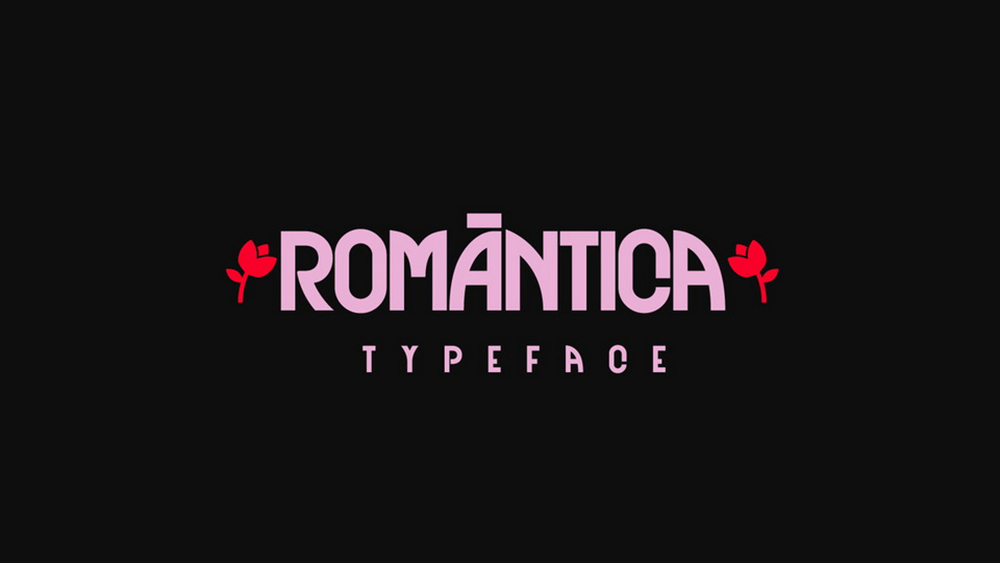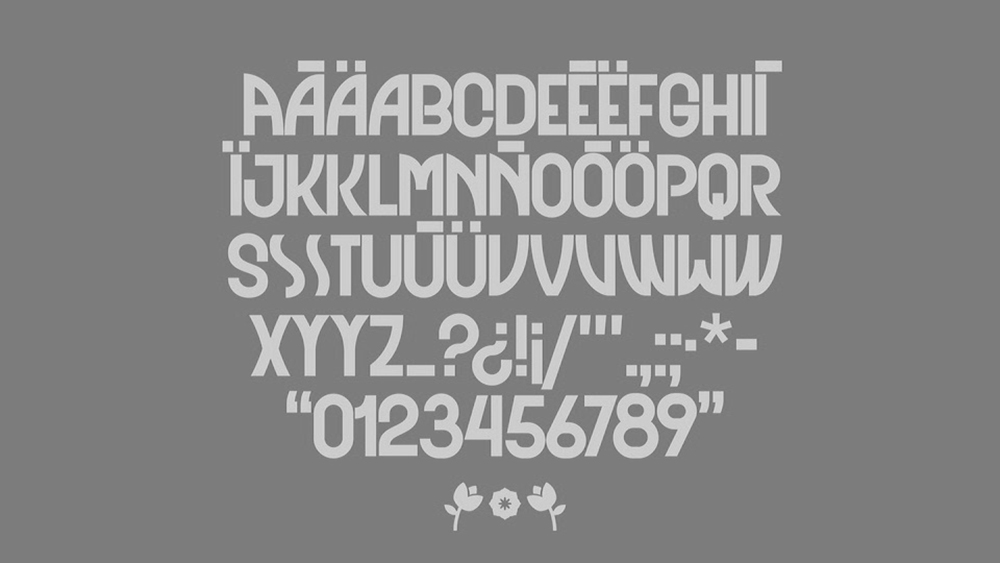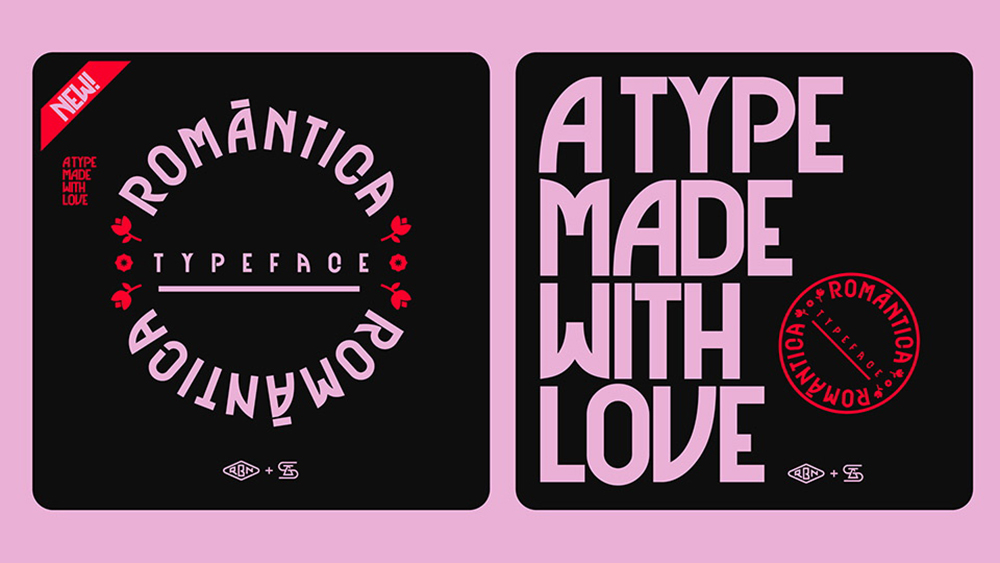
دانلود فونت انگلیسی Romantica Font
فونت پرمیوم و انگلیسی Romantica Font يک فونت مدرن به سبک آرت دکو است. اين فونت با الهام از تايپوگرافی دهه 60 و 70، ظرافت، تجمل و کمی مدرنيسم را به نمايش میگذارد. اين فونت برای اضافه کردن سبک و نمای کلی تيتر شما بسيار عالی است. و به طور خاص برای اين فونت، ما سبکی منحصر به فرد و حس مدرن طراحی کردهايم، بنابراين از ايجاد هر پروژهای که ايده اصلی شما را نشان میدهد، لذت ببريد.